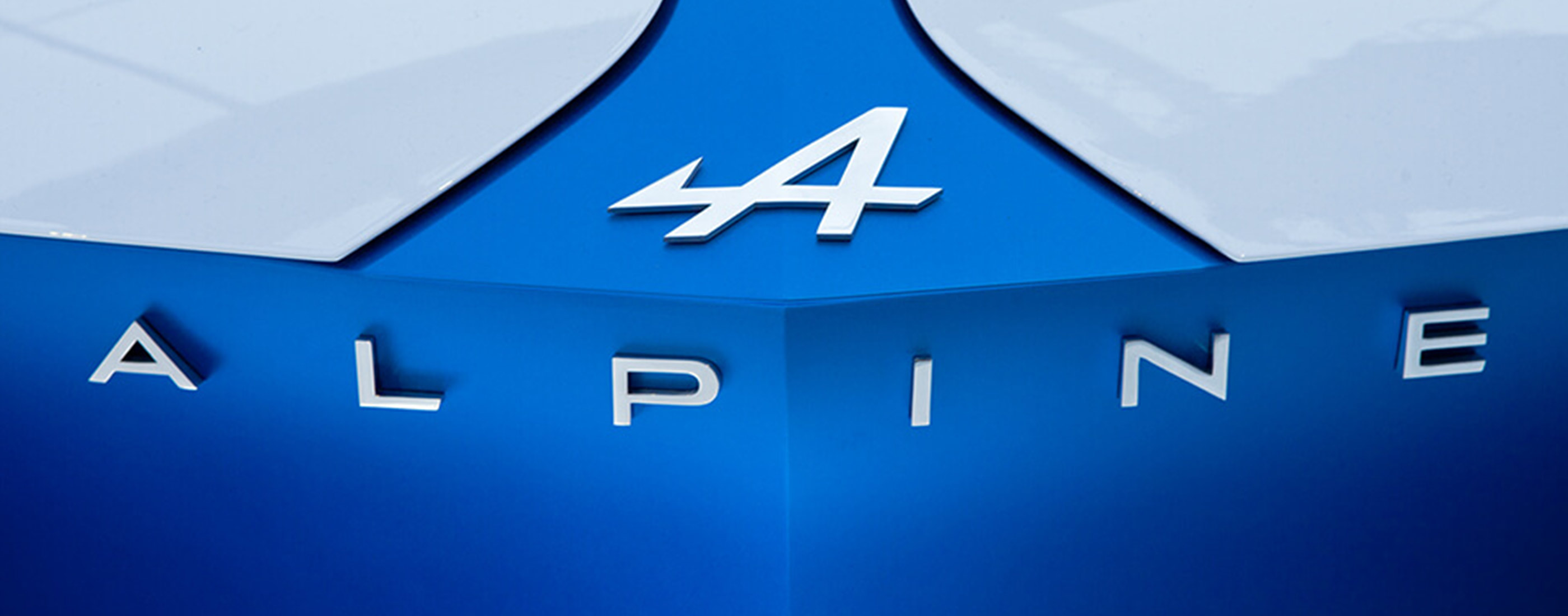
アルピーヌ フィットフォントプロジェクト
プロダクションタイプとの協業
Production Type (プロダクションタイプ) は、早くて楽しいをモットーとするフランスの伝統的な自動車メーカーであるAlpine (アルピーヌ) 社のために、包括的なフォントプログラム「Alpine Ascension」を開発しました。タイププロジェクトは、Alpine Ascensionファミリーに加わる日本語フォントとして、「Alpine AXIS」を提供しました。Alpine AXISは、フィットフォント技術により、Alpine Ascensionに合わせてAXIS Fontのウエイトを調整しています。タイププロジェクトが開発したフィットフォントは、フォントのウエイトやコントラスト、字幅を変更した場合でも、字画の比率が適正で常にバランスの取れた状態を保つ機能を備えています。
Alpine Ascensionを開発した、 プロダクションタイプの創業者であるJean-Baptiste Levée (ジーン・バプティスト・レビー)氏にお話をお聞きしました。
1. プロダクションタイプについて教えてください。
フランス パリを拠点としたデジタル タイプデザインの会社です。私たちは、デザインプロフェッショナル向けのリテールフォントのオンラインショップでの販売から、製造業、ハイブランド、ファッションやメディア業界向けのカスタムフォントの開発まで幅広く行なっています。
私は芸術性の表現として、歴史とテクノロジーを両立させるというアプローチで系統的に作業を行い、デザイナーにとって機能的であり使用範囲の広いプラットフォームとしてフォントを制作しています。これまでに、製造業や映画業界、ファッションや出版向けに100を超えるタイプフェイスをデザインし、多くの賞を受賞しています。また、海外でも紹介され、フランス国立図書館と国立芸術センター、シカゴのニューベリー図書館やヨーロッパのいくつかの印刷博物館で常設コレクションとして展示されています。
2. アルピーヌプロジェクトはどのように始まったのでしょうか。
私たちは、アルピーヌのリブランディングを依頼されました。最初に取り組んだのは、ブランド価値を引き出す新しい専用フォント開発のために、アルピーヌのロゴを変更することです。まず、ロゴの「A」の先端部分の長さと鋭さを修正し、角度を調整しました。最終的に、それまでのロゴデザインへの微妙な改良点を加えることで、先端部分の角度と斜めのラインのバランスが向上し、まとまり感のあるワイドサンセリフになりました。新しい書体となるAlpine Ascensionは、このロゴを基本としてタイプフェイスをデザインし、フォントセットとして拡張しました。
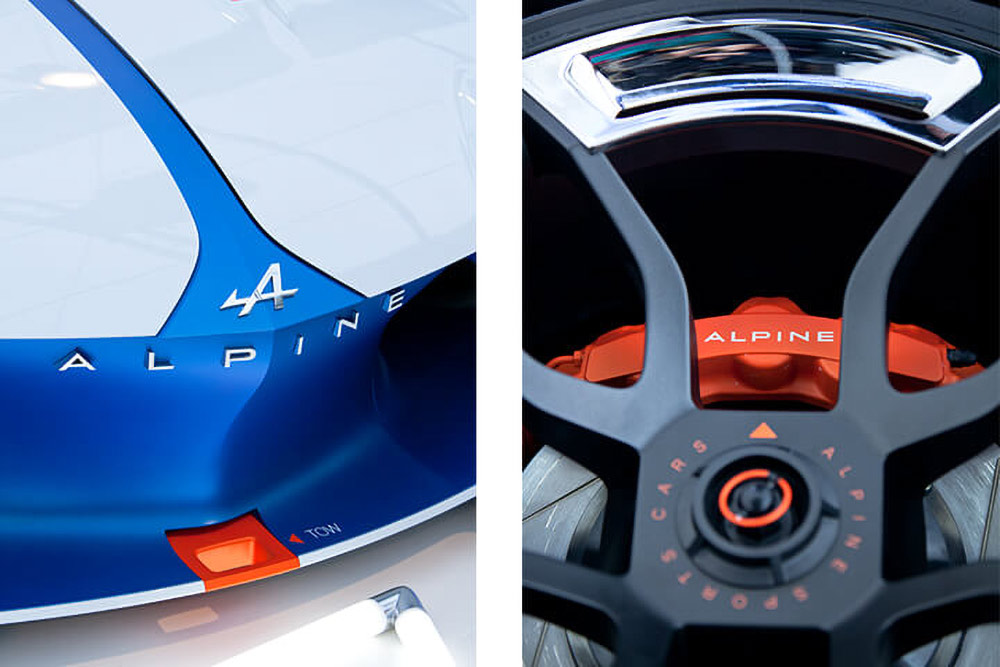
3. Alpine Ascensionについて教えてください。
アルピーヌ社の車は、スピード、軽快さ、軽量感などで知られていますので、これらの要素をフォントに反映しなければなりません。また、紳士に選ばれてきたということも重要なポイントでした。私たちは50年代と60年代のフランスの書体について調べるところから始めましたが、すぐに21世紀の書体として開発するという決定をしました。
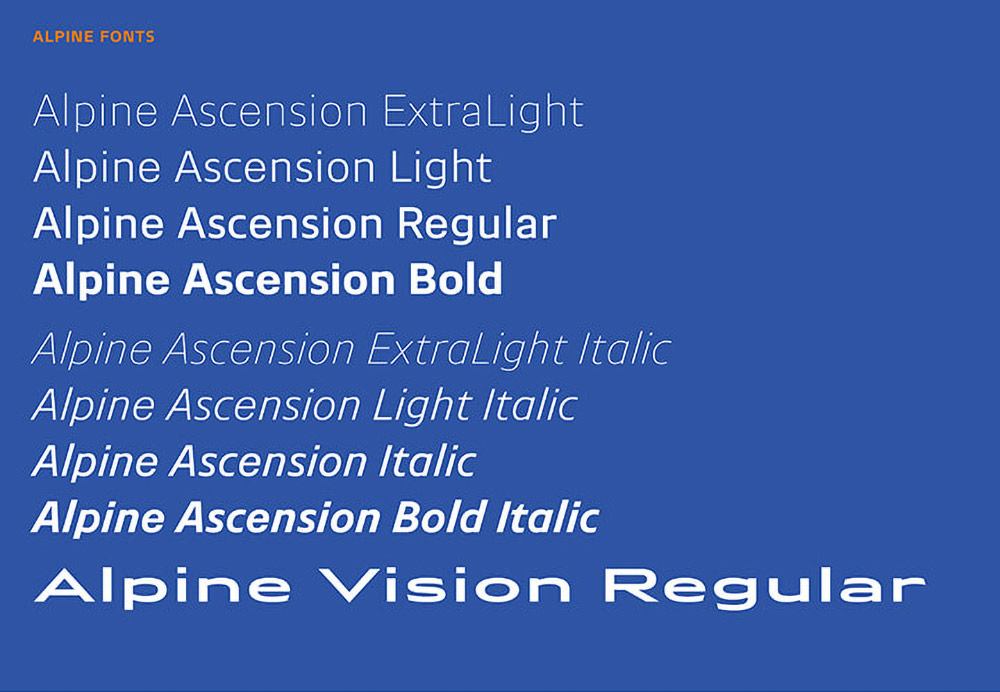
グローバル企業のためのフォントを開発するには、ラテン語以外の言語圏での使用を前提とする必要があります。アルピーヌ社の場合、最初に必要となる言語サポートは日本語でした。私たちは、タイププロジェクトのエキスパートと協業することで、Alpine Ascensionに合わせて調整したAXIS Fontを、Alpine AXIS として提供することができたのです。これにより、Alpine Ascensionファミリーは、アルピーヌ社のメッセージをヨーロッパ全土と日本に届けることができるようになりました。
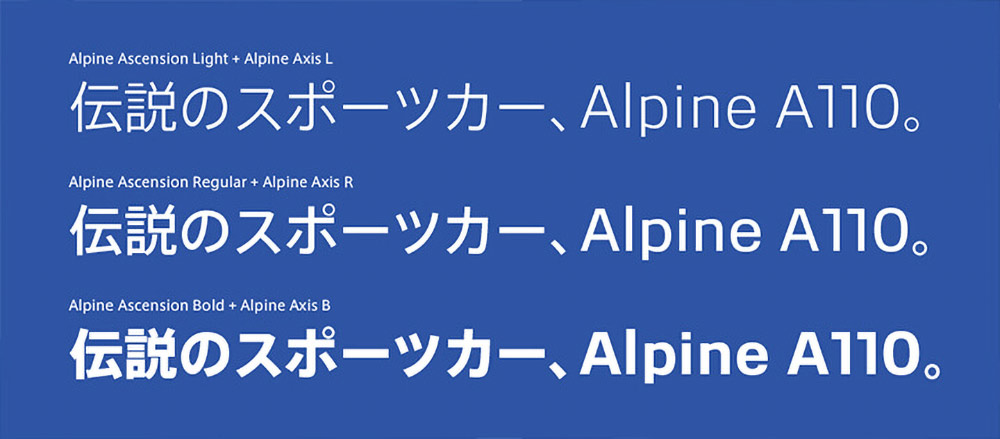
5. タイププロジェクトについて、そしてAlpine AXISについてどう思いますか?
可用性、コミュニケーション、価格の明快さ、対応の柔軟さといったいくつもの要素のバランスがとても良いと思っています。タイププロジェクトは、これらすべての項目において最高得点でした。この評価により、私たちがデザインしたフォントとスムーズにマッチさせるフォントとしてAXIS Fontを選択しました。
6. フィットフォントサービスについてどう思いますか?
フィットフォントが、ブランドの一貫性を保つための重要なポイントでした。フィットフォントは、リテールフォントとカスタムフォント双方を最大限に活用し、最適な価格で、お客様への完璧な提案を実現してくれました。高い品質を維持したまま、ブランドの声を日本市場に広げることを実現したのです。
7. フランス国内、または世界的なコーポレートフォント、ブランドフォントのトレンドについて教えてください。
ブランディング市場ではサンセリフ体が主流ですが、スクリプトフォントや表現力豊かなフォントも強いですね。カスタムフォント市場には、2つの傾向があります。私たちは、お客様に革新的であり、かつ長く使われる書体を提案しています。ですが、デザイン品質が高いとは言えない書体を短期間に提供するケースも目にします。